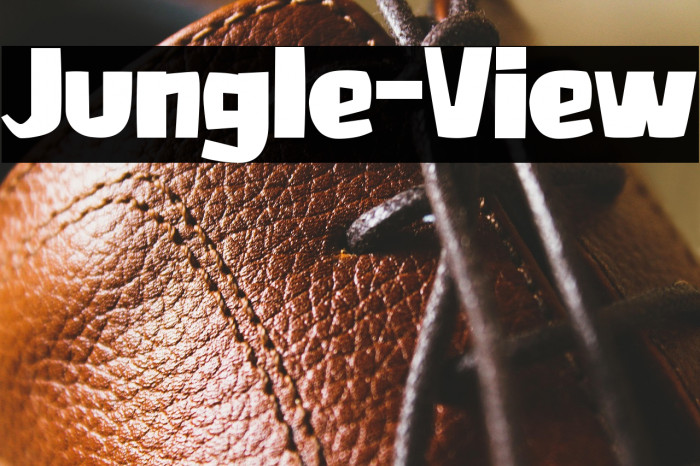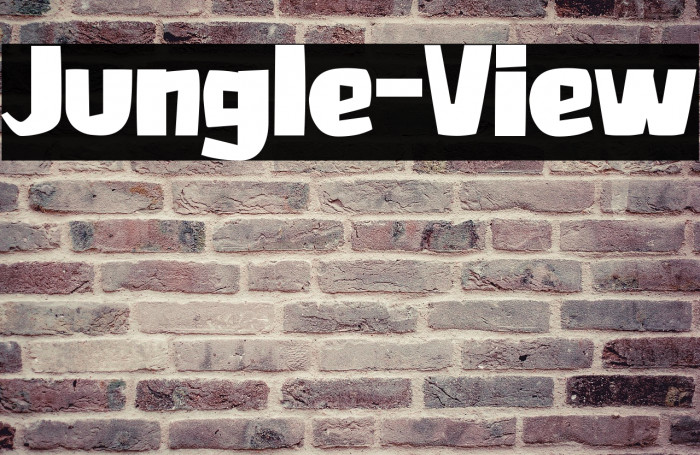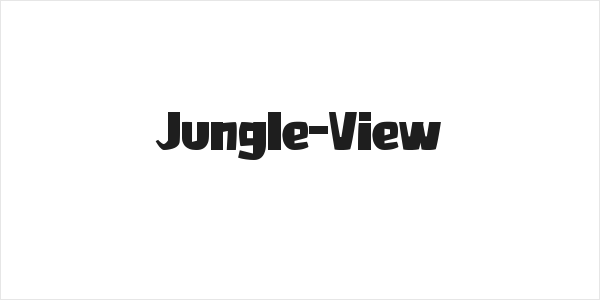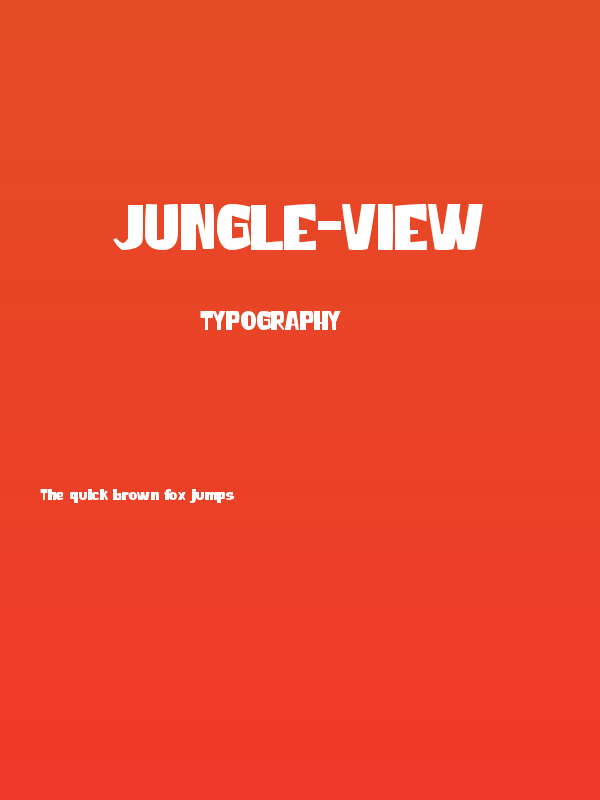
Jungle-View Font
| Estilo geral | Playful, Adventurous |
| Caso de uso | Headlines, Posters, Branding |
| Projetos propostos | Ideal for adventure-themed posters, children's book covers, playful branding, and eye-catching headlines. |